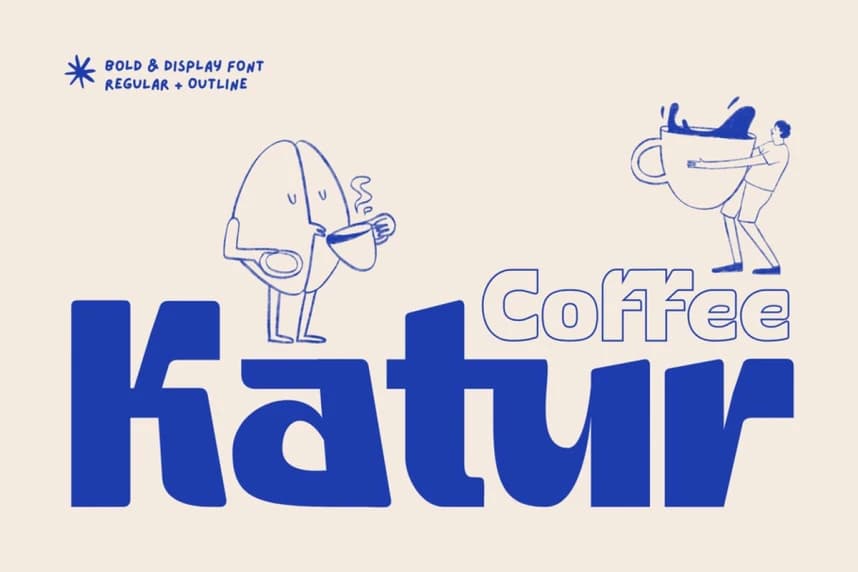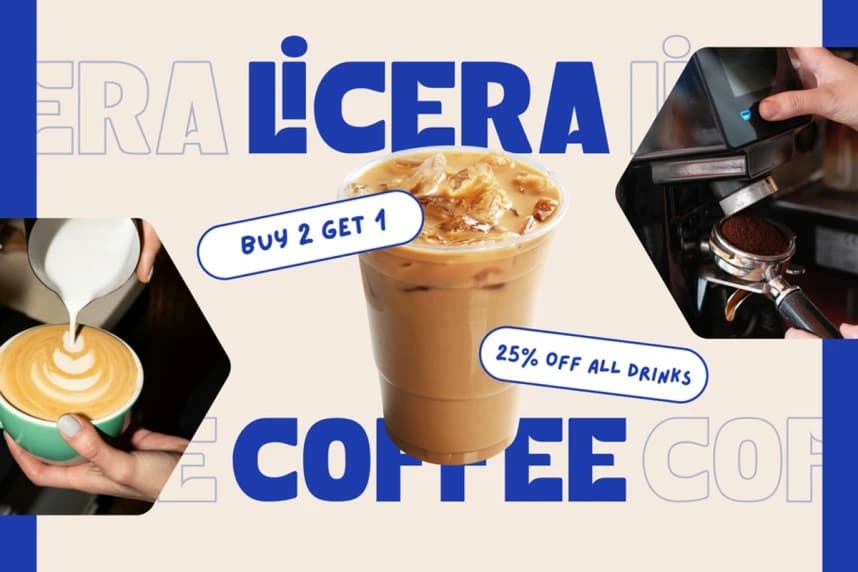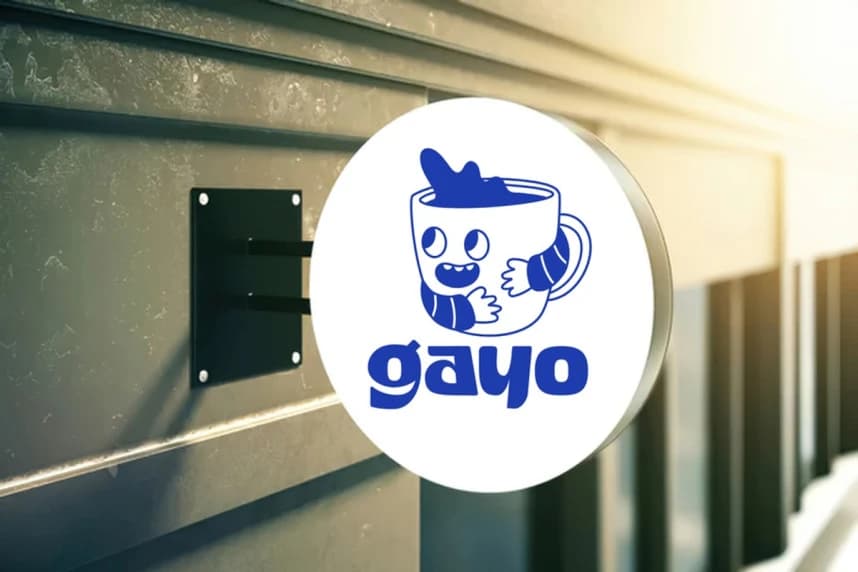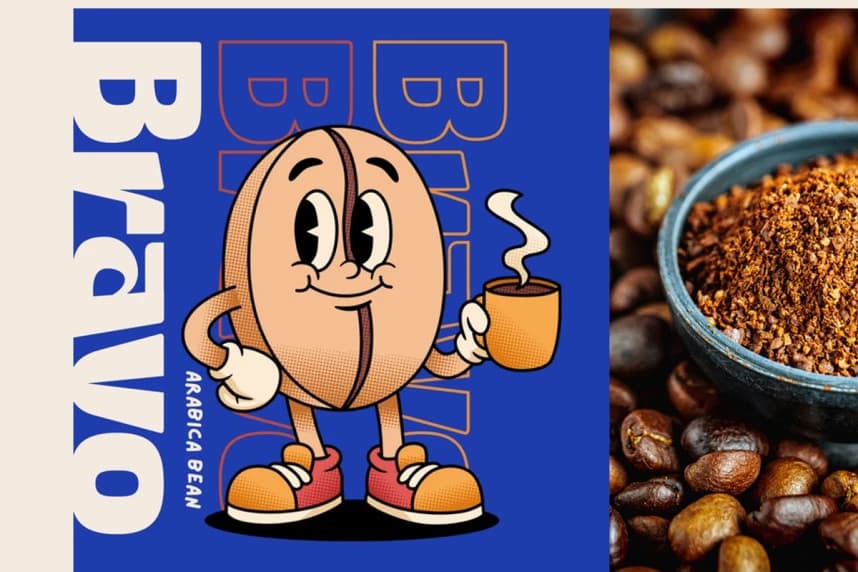
Katur Coffee Font
Katur Coffee Font, modern kahve markalarını canlandırmak için tasarlanmış cesur bir display sans fontudur. Temiz geometrik formlar ve şık bir kontur özelliğiyle öne çıkan bu font, logolar, menüler ve tanıtım tasarımları için taze fakat asi bir görünüm sunar.
Katur Coffee Font, modern kahve markalarını güçlendirmek için tasarlanmış cesur bir gösterişli sans fontudur. Şık bir kontur bonusuyla temiz geometrik formlara sahip olan bu font, logolar, menüler ve tanıtım tasarımları için taze ancak keskin bir görünüm sunar.
Katur Coffee